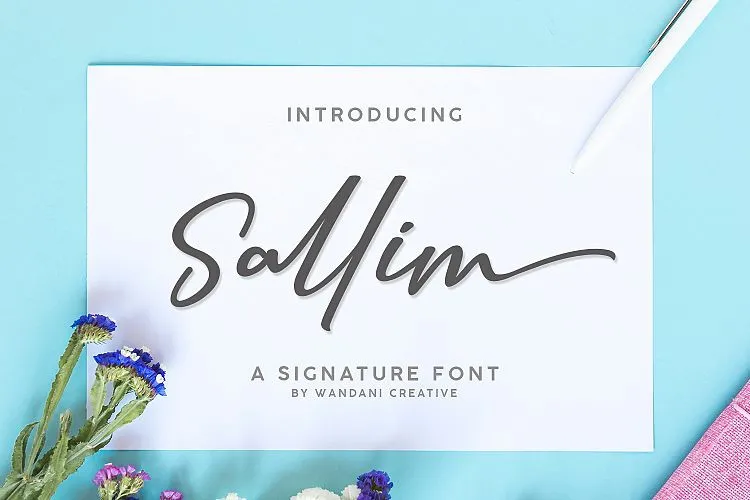
Sallim Signature Font – Download Grátis
Sallim Signature Font é uma elegante fonte script que destaca-se pela sua escrita cuidadosamente elaborada e movimentos fluidos dos lábios para criar linhas arredondadas suaves, tornando-a única e distintiva. Esta fonte é ideal tanto para criações de identidade visual como para aplicações em produtos ou comunicação de marca. Perfeitamente adaptável a logotipos, materiais de envio, outdoors, roupas, design de embalagens de produto, selos, convites de casamento, cartões de aniversário, mensagens de marca e layouts de sites, Sallim Signature Font traz um toque criativo para qualquer projeto. Com seu estilo fresco e único, esta fonte pode ser encontrada em muitos tipos de projetos, tornando-a uma escolha perfeita para designers buscando criar um design personalizado que destaca-se do resto.